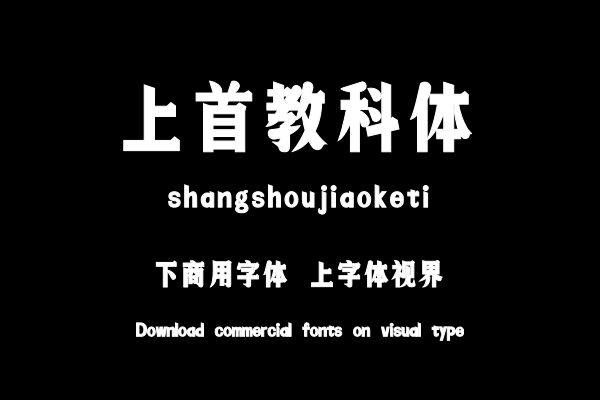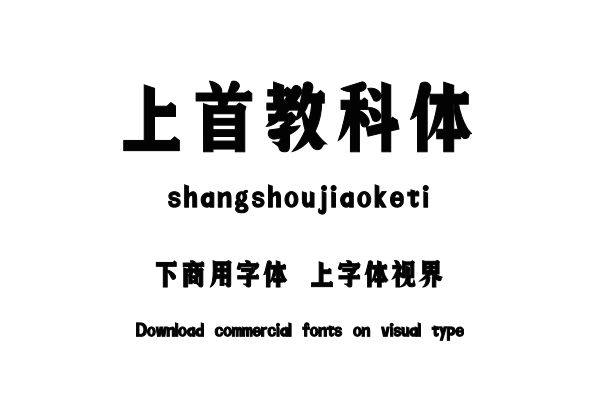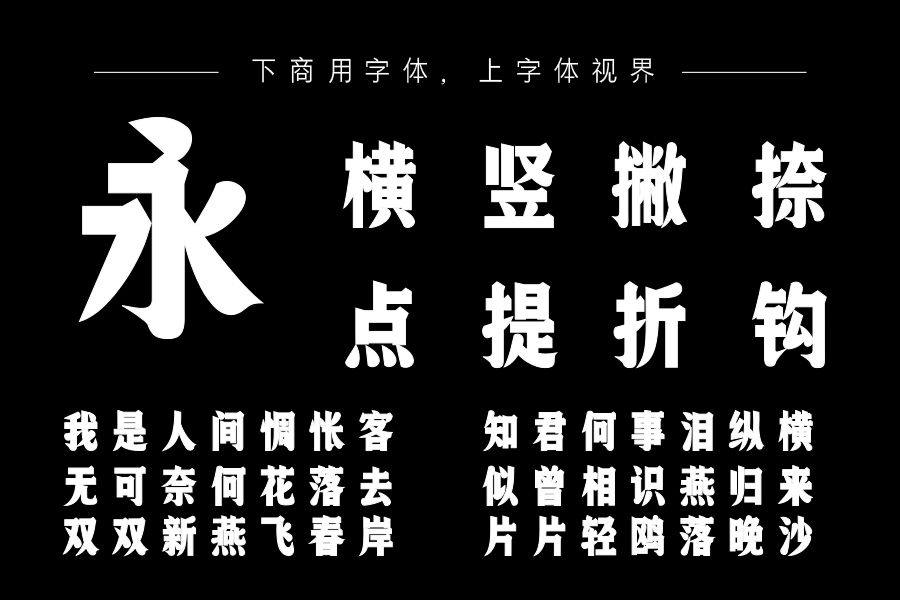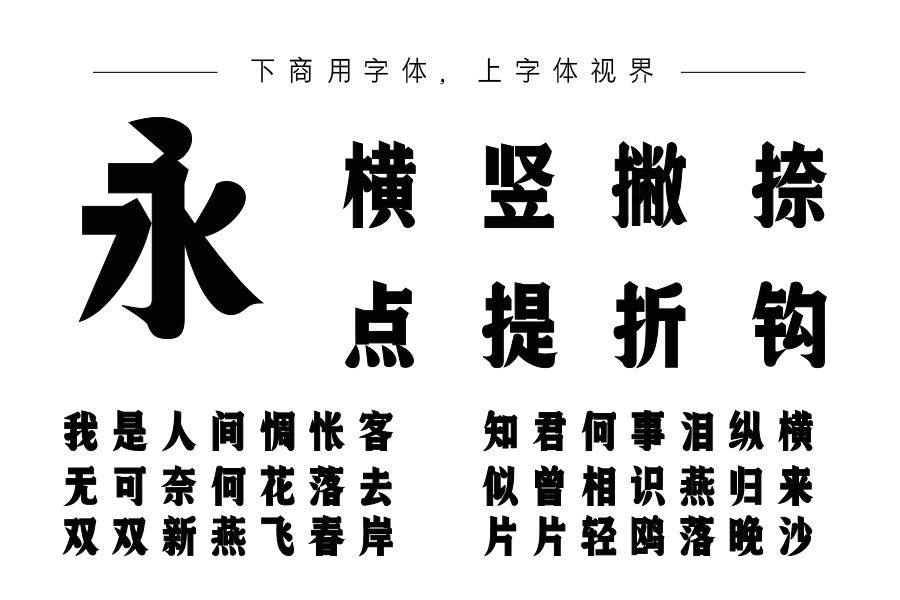
上首教科体,字体笔画端正。字如其名,具有满满的文学气息,犹如一位具有文化气息的学者在此站立,腹有诗书气自华,整体气息舒适。笔画流畅的同时也刚柔并济,笔锋尖锐且存......购买须知:“下载服务费”与“字体VIP”所获得字体 仅用于个人非商用, 商用请联系付费授权。本字体为电脑用字,手机没有root权限不支持直接手机换字(手机如何root,请自行百度搜索教程)。购买前请先 了解清楚后再付款 ,字体为虚拟产品无法回收 一旦购买不支持退款。